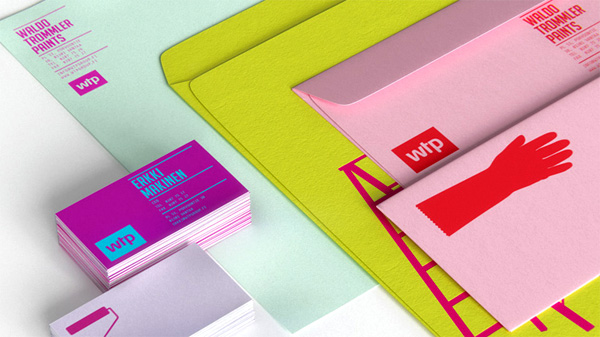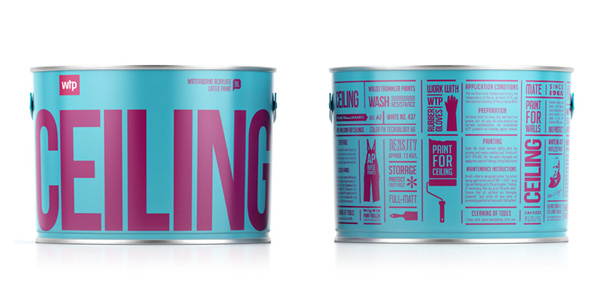
La agencia ucraniana Reynolds and Reyner, encabezada por los directores creativos Artyom Kulik y Alexander Andreyev, fue la encargada de diseñar la imagen corporativa de Waldo Trommler Paints, una pequeña compañía finlandesa fabricante y distribuidora de pinturas.
Identidad corporativa para Waldo Trommler Paints. Reynolds and Reyner, 2012.
El principal objetivo del cliente era conseguir una nueva identidad que destacara entre marcas similares ya existentes en el mercado. “No solo necesitamos destacar – ¡Tenemos que destacar!”; Reynolds and Reyner toma este concepto como el principio que va a estar presente a lo largo de todo el proyecto.
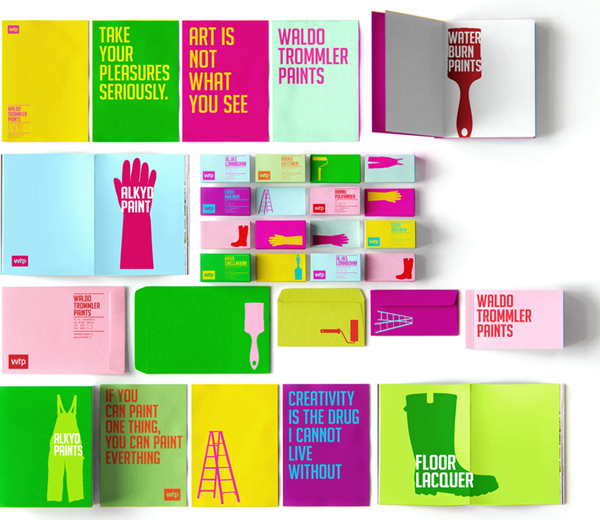
Identidad corporativa para Waldo Trommler Paints. Reynolds and Reyner, 2012.
Para ello utiliza un lenguaje muy visual, que es común en todos y cada uno de los elementos diseñados por el equipo de profesionales, desde tarjetas de contacto y sobres personificados hasta el packaging y los recipientes que contienen la pintura. Todas estas aplicaciones consiguen transmitir amabilidad, calidad e innovación, las principales características de la empresa, utilizando como herramienta la fusión de color y tipografía.
Aplicaciones en tarjetas y sobres. Identidad corporativa para Waldo Trommler Paints. Reynolds and Reyner, 2012.
El grafismo generado para representar a Waldo Trommler Paints en el mercado es simple y directo e interactúa con el cliente. No existe un color único que simbolice la marca, en cambio sí que se ha creado una tipografía propia para el logo corporativo que combina trazos horizontales, verticales y diagonales con circunferencias de distinto radio.
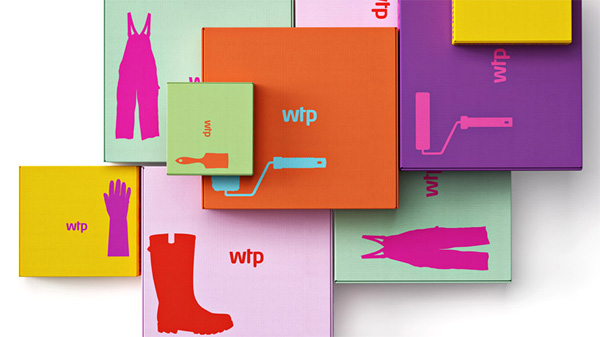
Aplicaciones en packaging para Waldo Trommler Paints. Reynolds and Reyner, 2012.
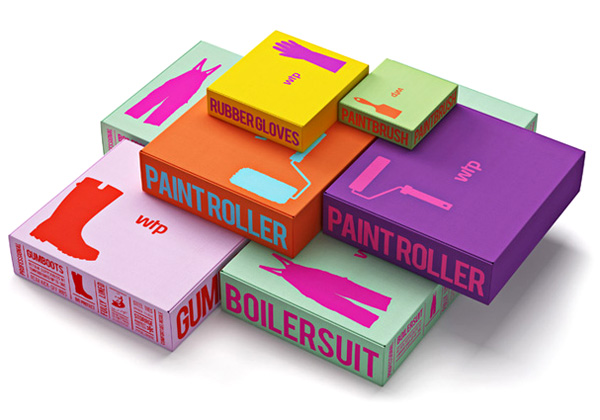
Aplicaciones en Packaging para Waldo Trommler Paints. Reynolds and Reyner, 2012.
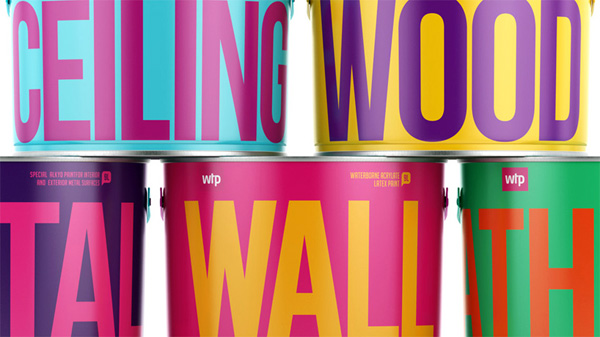
Identidad corporativa para Waldo Trommler Paints. Reynolds and Reyner, 2012.